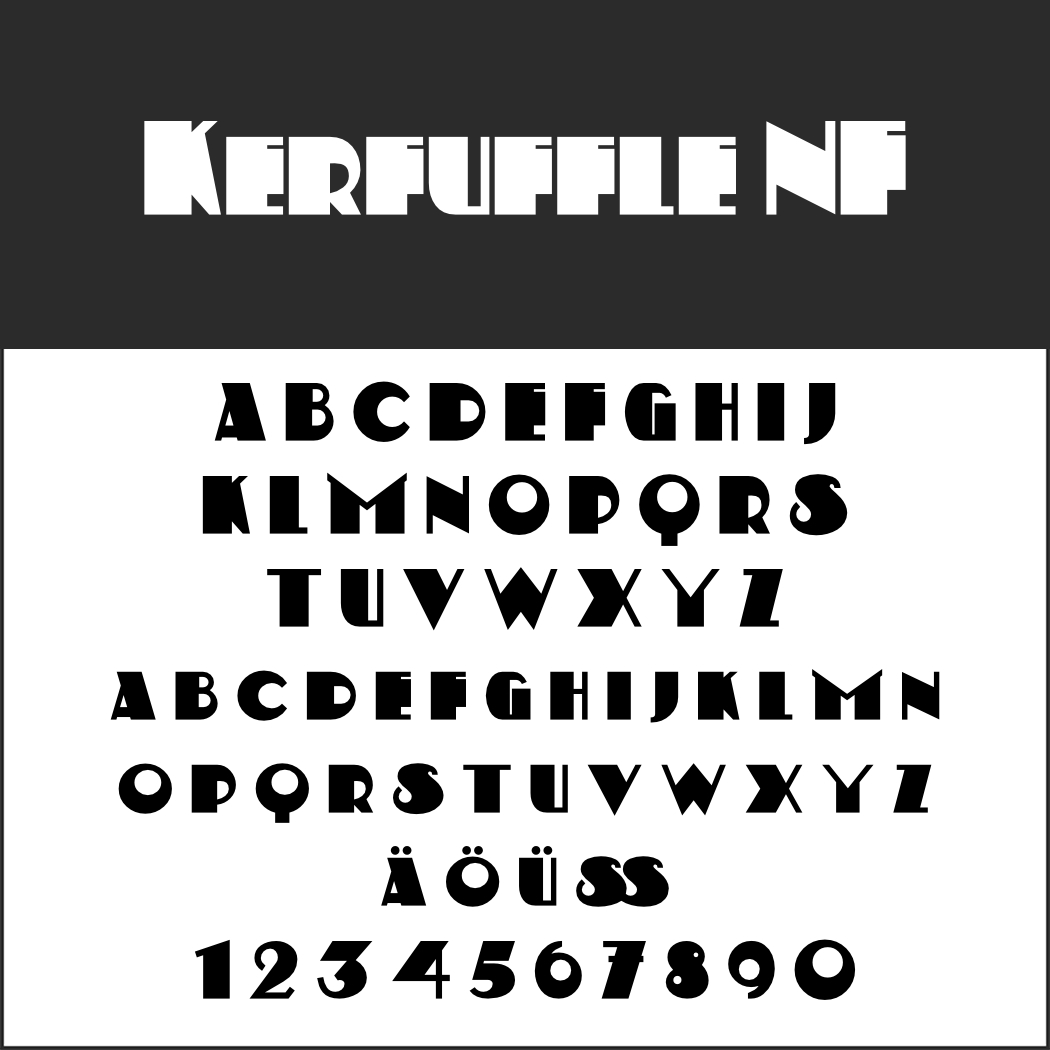
Wenn Schriftarten fett auftreten, haben sie meist etwas Wichtiges zu sagen. Sie heben dann einzelne Wörter hervor, die in nicht-fettem Text stecken. Manchmal soll aber auch etwas mehr „fett rüberkommen“: Überschriften, Logos, Schlagwörter und Slogans beispielsweise. Dann wollen wir nicht einfach nur die Bold-Schriftstärke nutzen, sondern einen Font, der insgesamt fett auftritt. Ein paar Prachtexemplare in dieser Hinsicht finden Sie in unserer Auswahl an Gratis-Fonts.
Alfa Slab One
Der chilenische Designer greift eine Schrift auf, die Robert Thorne 1921 für die Thorowgood Foundry entwarf.
Bigfish
Als Vorbild für die Serifenschrift eines Kölner Designstudios dienten alte Zirkusplakate.
Curvilingus
Curvilingus ist nicht nur fett, sondern in jeder Hinsicht üppig. Eignet sich für alle emotional besetzten Retro-Themen.
Daggersquare
Die futuristische, geometrische Schriftart aus Kolumbien gibt einen aufmerksamkeitsstarken Display Font ab.
Facile Sans
Der schnörkellose geometrische Font aus Indonesien ist für Headlines und Logos optimiert.
- Besonderheit: keine Kleinbuchstaben
Fattern
Die weichen Buchstaben bieten sich für eine farbige Gestaltung an.
- Besonderheit: keine Kleinbuchstaben und keine deutschen Sonderzeichen
Fette Bauersche Antiqua
Die handgefertigte Vorlage für diesen Font stammt aus den 1950er Jahren. Neben dieser Shadow-Variante gibt es die Fette Bauersche Antiqua auch in Regular und Outline.
Kerfuffle NF
Die goldenen Zwanziger lassen grüßen: Kerfuffle NF basiert auf einem Poster des niederländischen Designers C. J. van der Hoef aus dem Jahr 1920.
- Besonderheit: keine Kleinbuchstaben, kein ß
- Design: Nick Curtis
Multicolore Pro
Multicolore Pro entfaltet seine gesamten (farbigen) Möglichkeiten mit einem modernen Bildbearbeitungsprogramm.
- Besonderheit: keine Kleinbuchstaben, kein ß
Nacimiento
Nacimiento (spanisch für: Geburt) lebt von scharfen Kontrasten und ist für Plakate, Schilder und Werbebanner konzipiert.
Santhony
Etwas nachlässig mit der Feder geschrieben: Diesen Eindruck erweckt der indonesische Font für auffällige Schlagwörter.
Wobbles
Fluffig, wie Kaugummiblasen: Wobbles ist richtig fett, am besten für kurze Headlines.
- Besonderheit: keine Kleinbuchstaben